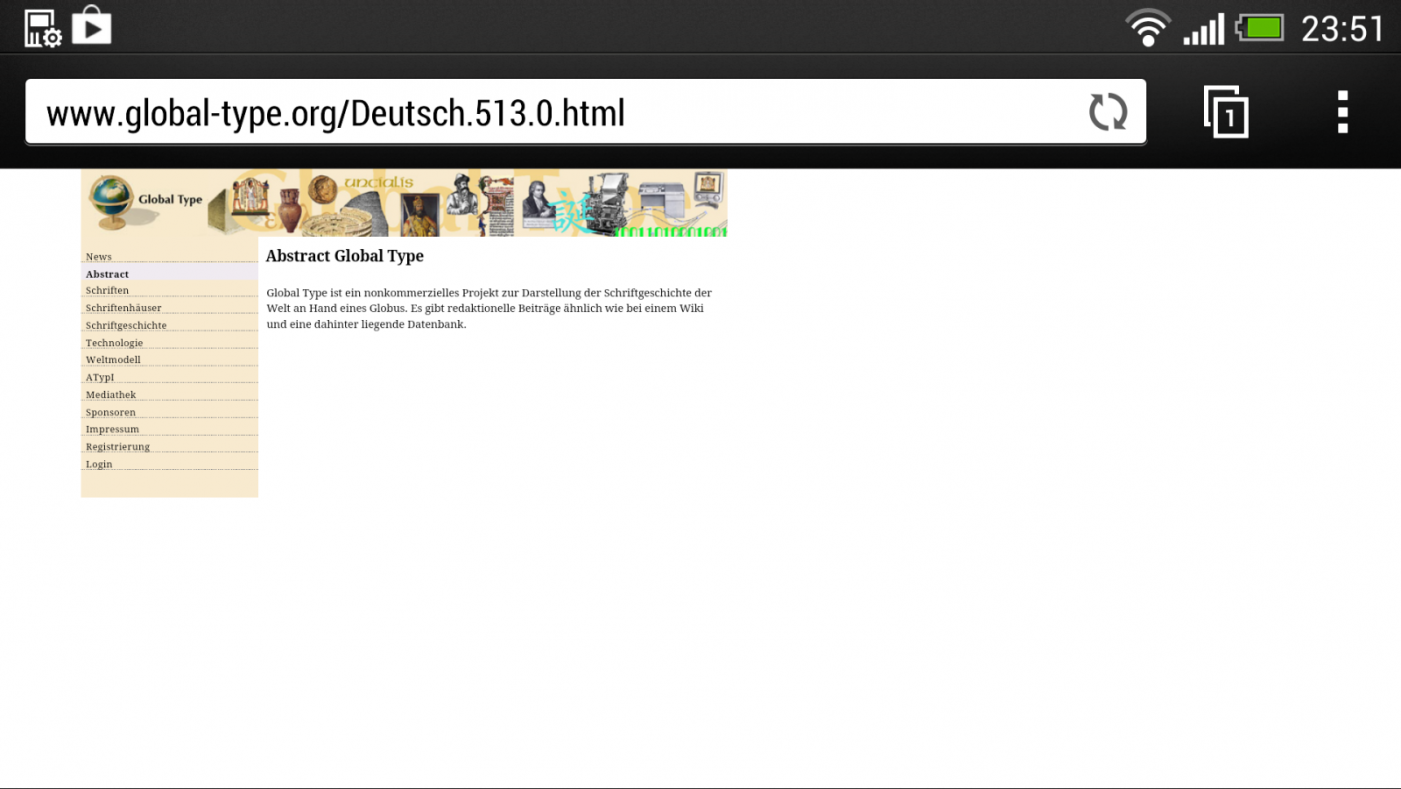
[GlobalType] Spalte „similar to“
Es erhebt sich für mich die Frage, ob nicht doch die Spalte „similar to“ der Schriftdatenbank von GlobalType freigeschaltet werden sollte. Natürlich wäre es dann möglich, sich die Namen von Clones eines Original zu holen – deren Einsatz und Entwicklung aber ohnehin gegen geltendes Recht verstoßen. Das weiß man doch. Aber da die entsprechenden „schwarzen Listen“ doch ohnehin schon seit Jahren durch das Internet geistern, wäre das doch im Grunde heute auch kein Verlust mehr. Kein Profi, der etwas auf sich hält oder gar selbst Schriften zeichnet, wird Clones verwenden.
Mit dem Relaunch könnte ich diese Spalte zugänglich machen, nur wollte ich das vorher mit Euch diskutieren. Also, was meint Ihr: Sollte ich das tun oder eher nicht? Wenn nein, warum nicht?
Die Klone oder alternative Interpretationen können ihren Wert haben, sofern sie besser ausgebaut sind. Wenn ich die Wahl zwischen FF DIN oder PF DIN hätte, würde ich die von Parachute nehmen, da sie polytonisches Griechisch kann (Sorry Albert-Jan ;)).
Oder fasse ich den Begriff Klon zu weit?
Natürlich wäre es dann möglich, sich die Namen von Clones eines Original zu holen
Solange du die Klone nicht zum Verkauf anbietest, ist das Informieren darüber doch kein Problem. Es lässt sich ja umgekehrt insbesondere dazu benutzen, dass man erfährt, dass einem Klon ein anderer Font zu Grunde liegt und man kann dann stattdessen auf diesen zurückgreifen.
– deren Einsatz und Entwicklung aber ohnehin gegen geltendes Recht verstoßen.
Was aber natürlich immer Fallentscheidungen sind. Die bekanntesten Klone sind ja die Bitstream-Klone (Humanist XXX, Swiss, Zurich etc.) von Linotype-Schriften (Frutiger, Helvetica, Gill, Univers ...). Diese verstoßen aber nicht (mehr) gegen geltendes Recht. Die Unternehmen hatten sich schon vor langem darüber geeinigt und Bitstream hat also im Nachhinein die offizielle Lizenz erhalten, diese Schriften Unterlizenzieren zu dürfen. (Heute sind Bitstream und Monotype ja ohnehin Teil von Monotype und es gibt da gar keinen Wettstreit mehr.)
Und unabhängige Digitalisierungen alter Schriften (siehe DIN-Schriften) sind ohnehin keine Klone, sondern einfach ähnliche Schriften.
@ Phoibos: Ein Klon ist eine illegale Raubkopie einer Schrift. Da beißt die Maus keinen Faden ab. So etwas hat es schon im Blei gegeben, und da hat es im Laufe der Jahre bestimmt schon genügend Prozesse gegeben. Verschärft hat sich das Problem im Fotosatz durch die Notwendigkeit für die Hersteller, möglichst alle angesagten Schriften im Repertoire zu haben. Und seit Schriften digital geworden sind, ist das Problem endgültig zum Höllenritt mutiert. Das liegt u.a. daran, dass es in den uSA nicht möglich ist, das Aussehen einer Schrift zu schützen, nur deren namen. So wird für die Kreation einer Schrift nicht wie bei uns eine Schöpfungshöhe eingeräumt, sondern nur ein Markenzeichen für den Namen ermöglicht. Das ist im internationalen Recht auch heute nicht einheitlich geregelt, schon gar nicht weltweit.
Ein Beispiel dafür, was in der Spalte „similar to“ eigentlich zu finden ist: Bei der Aachen Bold von Colin Brignall steht da drin:
Adobe/Autologic/Bitstream/Castcraft/Compugraphic/FC/Fotostar/Hell/LaCache/Linotype/Monotype/Purup/Scangraphic/URW/VGC
Diese Firmen haben die Schrift also entweder lizensiert oder nachgeahmt, das wäre im Einzelfall zu überprüfen. Ein weiteres Beispiel:
nach Avant Garde Gothic
steht da für die Century Gothic in „simlar to“. Das bedeutet, dass Herr Reichardt der Meinung ist, diese Schrift sei der Avant Garde Gothic nachgeahmt.
Das liegt u.a. daran, dass es in den uSA nicht möglich ist, das Aussehen einer Schrift zu schützen, nur deren namen.
In den USA werden Fonts heute als Computerprogramm geschützt. Das klingt aus europäischer Sicht etwas seltsam, aber kommt im Prinzip auf das gleiche heraus wie bei uns. Beim Schutz hierzulande geht es schließlich auch vornehmlich um das Design wie es sich IM Font manifestiert.
Am Montag erscheint ein weiterer Artikel meiner Schriftlizenzserie, da wird das noch einmal ausführlich besprochen.
Ein Beispiel dafür, was in der Spalte „similar to“ eigentlich zu finden ist: Bei der Aachen Bold von Colin Brignall steht da drin:
Adobe/Autologic/Bitstream/Castcraft/Compugraphic/FC/Fotostar/Hell/LaCache/Linotype/Monotype/Purup/Scangraphic/URW/VGC
Mhh, nur die Namen der Unternehmen? Das sagt natürlich wenig aus. Alle diese Unternehmen boten/bieten irgendwas »ähnliches« an? Zumindest der Name der betreffenden Varianten wäre hilfreich.
@ Ralf: Selbstverständlich werde ich die Klone nicht zum Verkauf anbieten. Die Originale übrigens auch nicht. Gar keine Schrift. Das Projekt soll herstellerneutral bleiben. Es gibt allenfalls Links zu Bezugsquellen. Das würde ich aber nicht selbst machen, da zu diesem Zweck nun wirklich genügend Quellen im Netz zu finden sind.
Da soviel in besagter Spalte drin steht, werde ich sie aber wohl nicht in der Ergebnistabelle von „Schriften suchen“ platzieren, sondern hier:
http://www.global-type.org/Suche-nach.566.0.html
(Besagte Seite dient übrigens schon seit 2004 „nur zu Testzwecken“ :mrgreen:  ). Aber ich glaube, da passt es besser, auch wenn z.T. auch ergänzende Info in dieser Spalte steht.
In den USA werden Fonts heute als Computerprogramm geschützt.